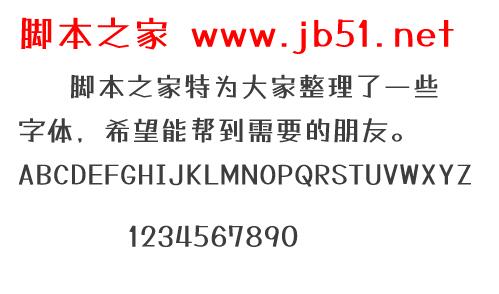
Tanugo漫畫體是一款基于Tanugo手寫體進(jìn)行字?jǐn)?shù)補(bǔ)全的免費(fèi)商用手寫字體。適合應(yīng)用于藝術(shù)設(shè)計(jì)、平面宣傳設(shè)計(jì)、網(wǎng)頁(yè)設(shè)計(jì),書法字帖等領(lǐng)域
原版其實(shí)有4個(gè)字重,但是利用原版字重來進(jìn)行補(bǔ)字是十分頭疼的,因?yàn)槟壳安]有類似風(fēng)格的大字庫(kù)可以補(bǔ)這款字。只能彎道超車,利用原版regular字重為模板,然后用兩款黑體大改,盡量接近Tanugo。然后再重新渲染制作獨(dú)立的粗體以及細(xì)體字重。